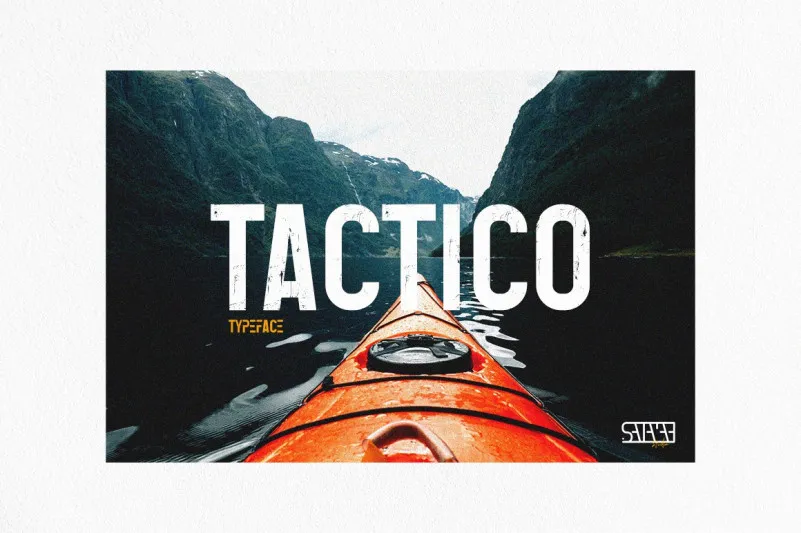
Esta fonte ‘Tactico Font’ é perfeitamente indicada para uso em aplicações visuais que exigem uma aparência moderna e elegante. Ela foi criada pela Salamah Studio, especialista em letras sem serifas. Com seu estilo all caps, a Tactico Font se destaca quando usada em banners de propaganda ou impressões de qualidade. Suas linhas clean e retas tornam-a perfeita para criações visuais contemporâneas que desejem um ar sofisticado. Essa fonte é uma escolha ideal tanto para projetos gráficos quanto para design editorial, sendo ideal para aplicação em materiais como cartazes, fliers ou qualquer outra publicidade visual. A Tactico Font não apenas adicionará profundidade e estilo a seus trabalhos, mas também oferecerá uma infinidade de possibilidades criativas. Experimente essa fonte na próxima vez que precisar de um design revigorante e moderno.